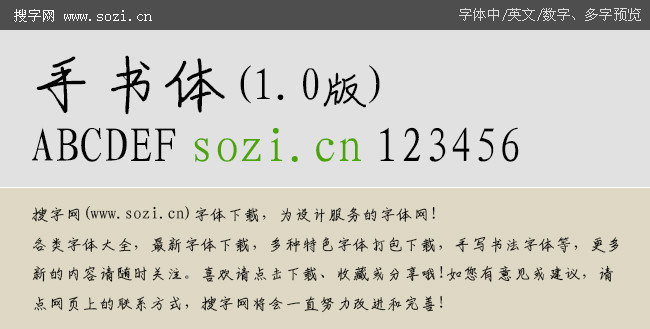
手書(shū)體
搜字網(wǎng)提供一款手書(shū)體中文字體下載,手書(shū)體是一款漂亮的手寫(xiě)風(fēng)格書(shū)法字體。由站酷ID為Joker9的一名北京平面設(shè)計(jì)師制作,字體風(fēng)格為手寫(xiě)風(fēng)格,可以用于slogan、banner、海報(bào)、商標(biāo)等設(shè)計(jì)。共做了基本漢字6763個(gè),提供給大家免費(fèi)商用。